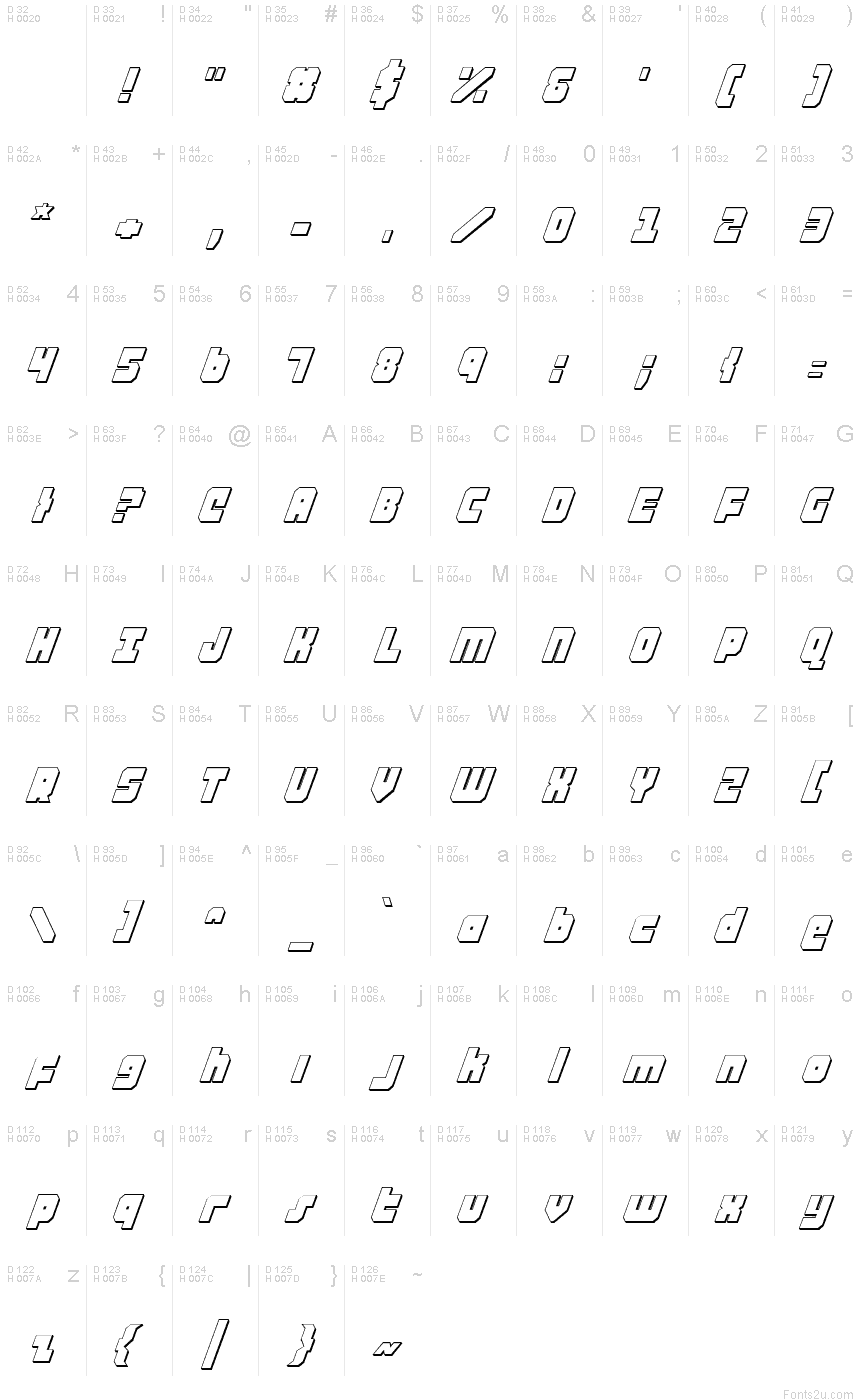
Alpha Taurus 3D Italic od Iconian Fonts to darmowy krój typu display o technologicznym charakterze i wyraźnych konturach. Dzięki dynamicznemu pochyleniu i masywnym, wyciągniętym krawędziom, stylistyka ta idealnie wpisuje się w klimat gier arcade i science-fiction. Litery wyglądają, jakby zostały wycięte z twardych paneli, a szerokie geometryczne kształty, ostre kąty i głębokie cieniowanie nadają krojowi wyrazistego, niemal mechanicznego charakteru.
Font naturalnie odnajduje się w logo gier, nagłówkach plakatów, czołówkach, okładkach albumów i ulotkach, gdzie futurystyczna energia lat 2000. wzmacnia przekaz. Jako darmowy krój świetnie sprawdza się również w krótkich nagłówkach i znakach graficznych, ponieważ ciężki kontur 3D sprawia, że nawet kilka słów nabiera wyglądu gotowej grafiki.